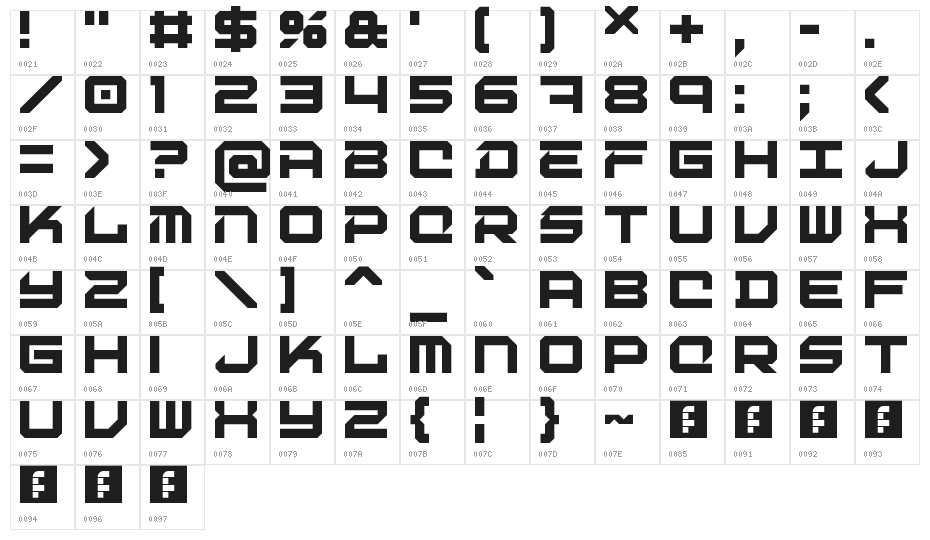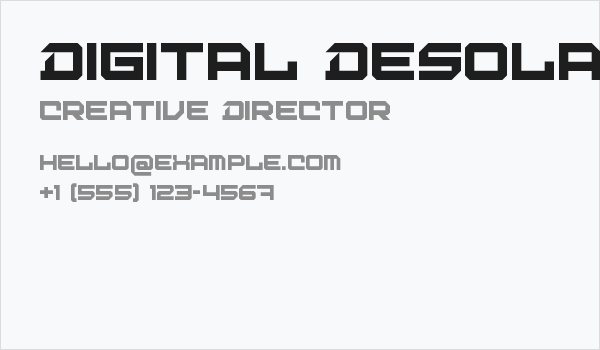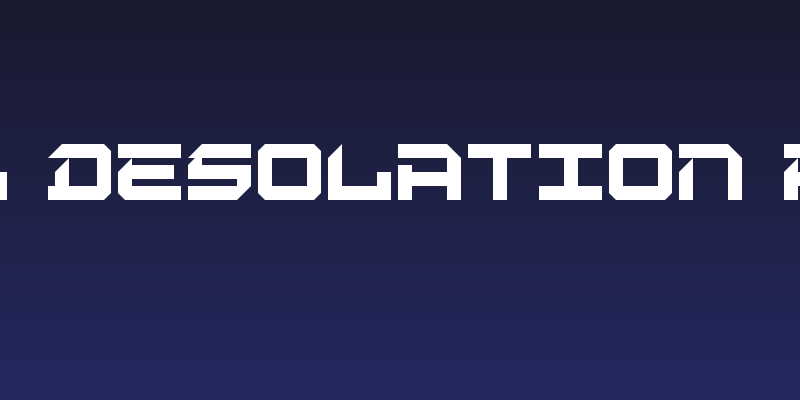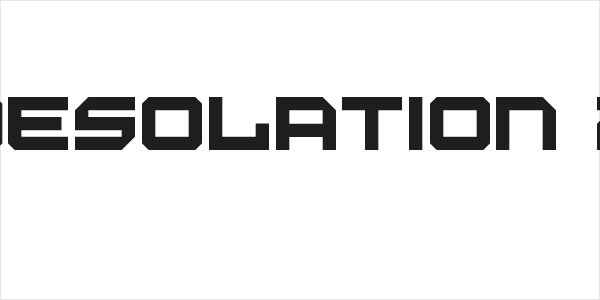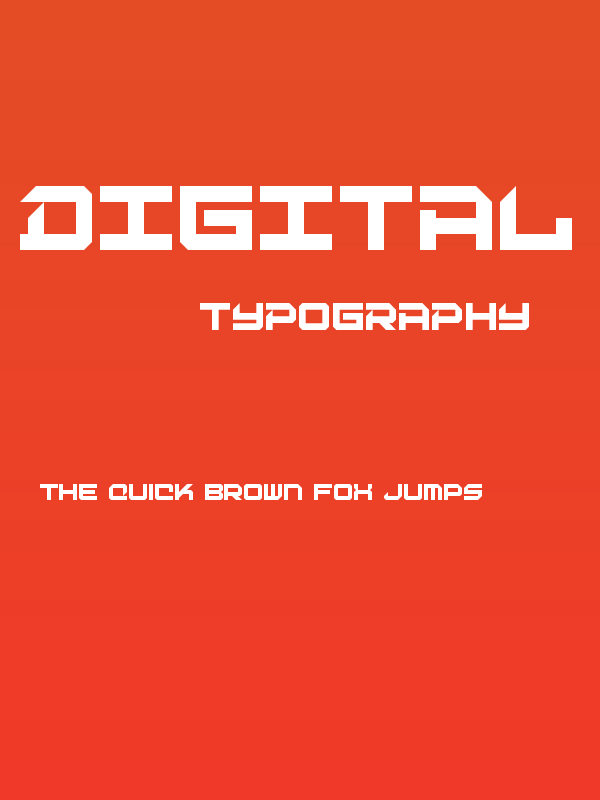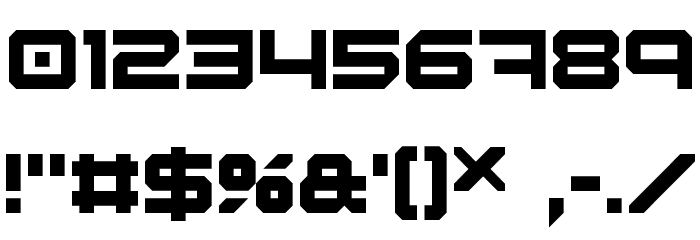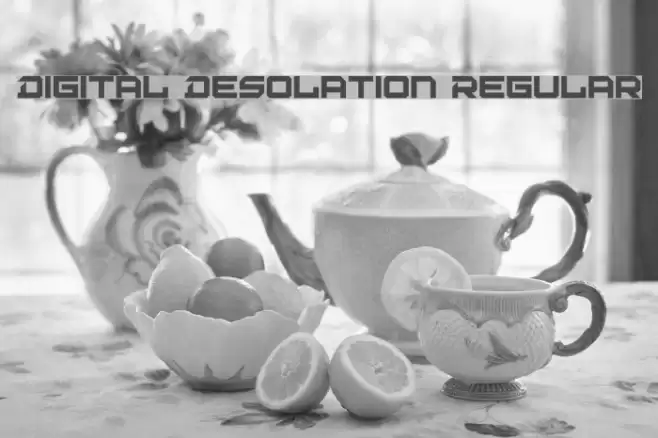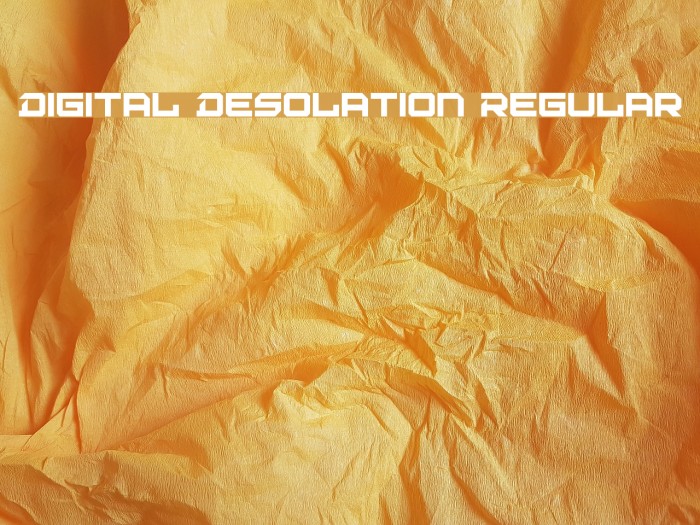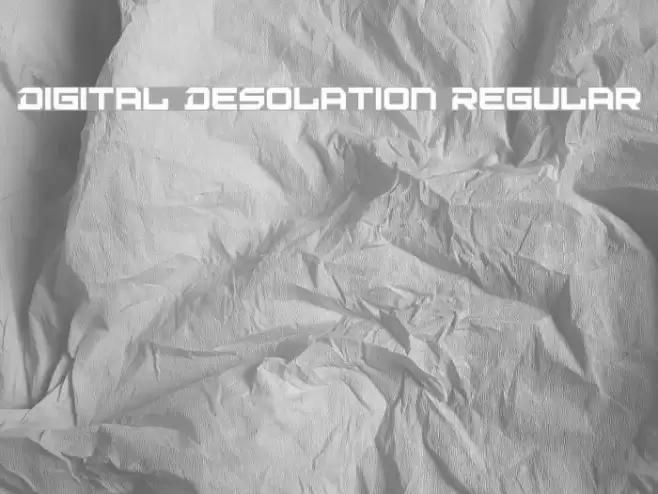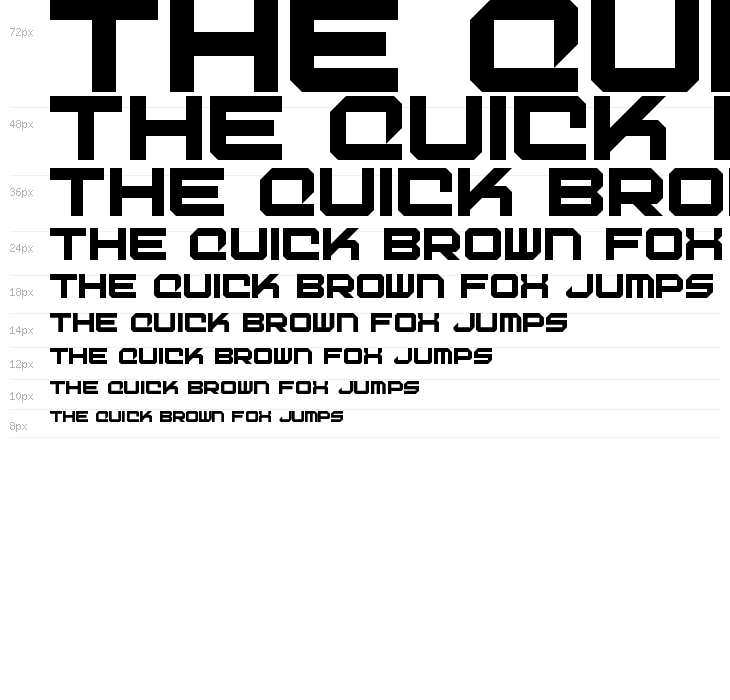
Digital Desolation Regular Font
| Progetti proposti | Ideal for technology-themed projects, video game titles, sci-fi movie posters, and digital interfaces. |